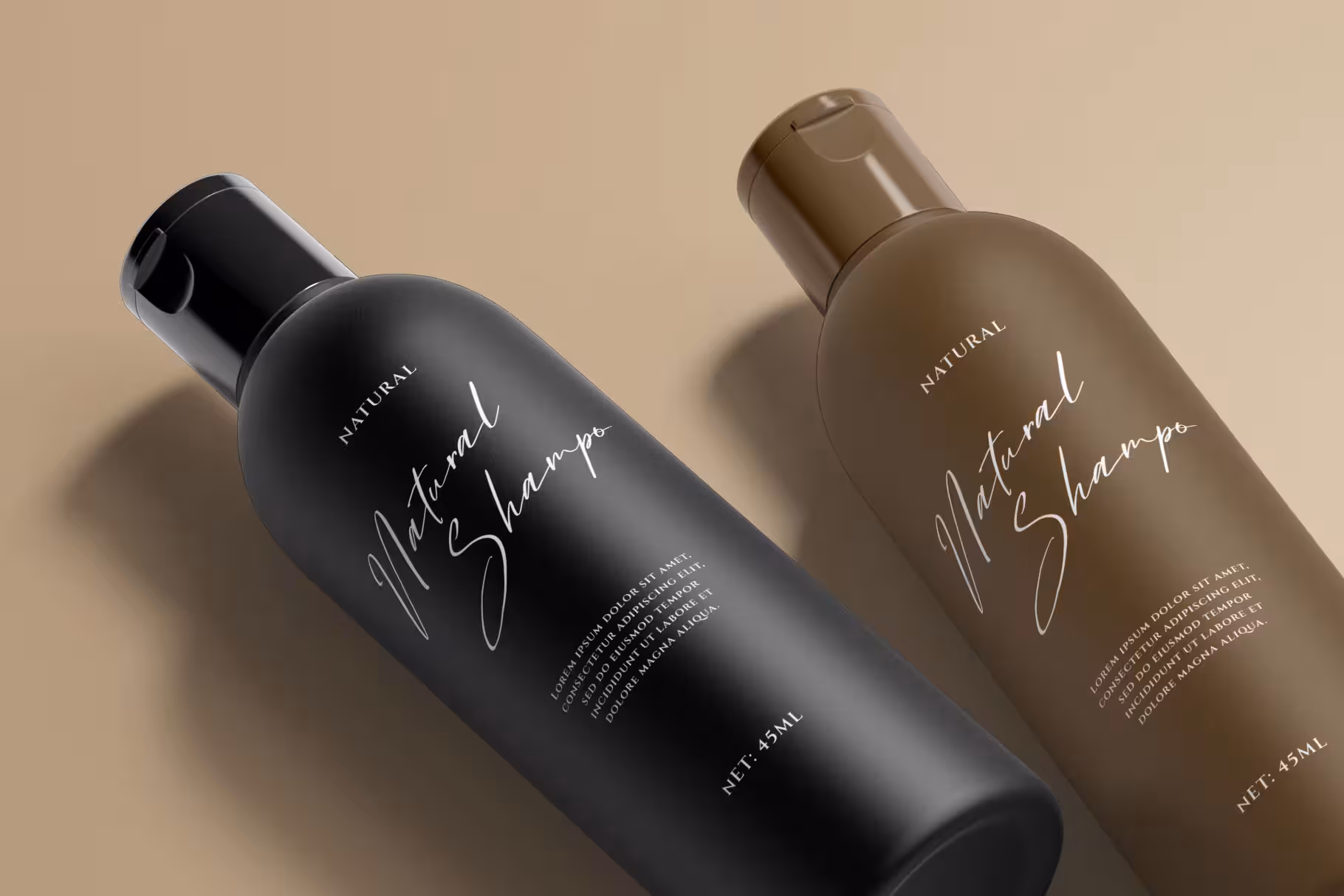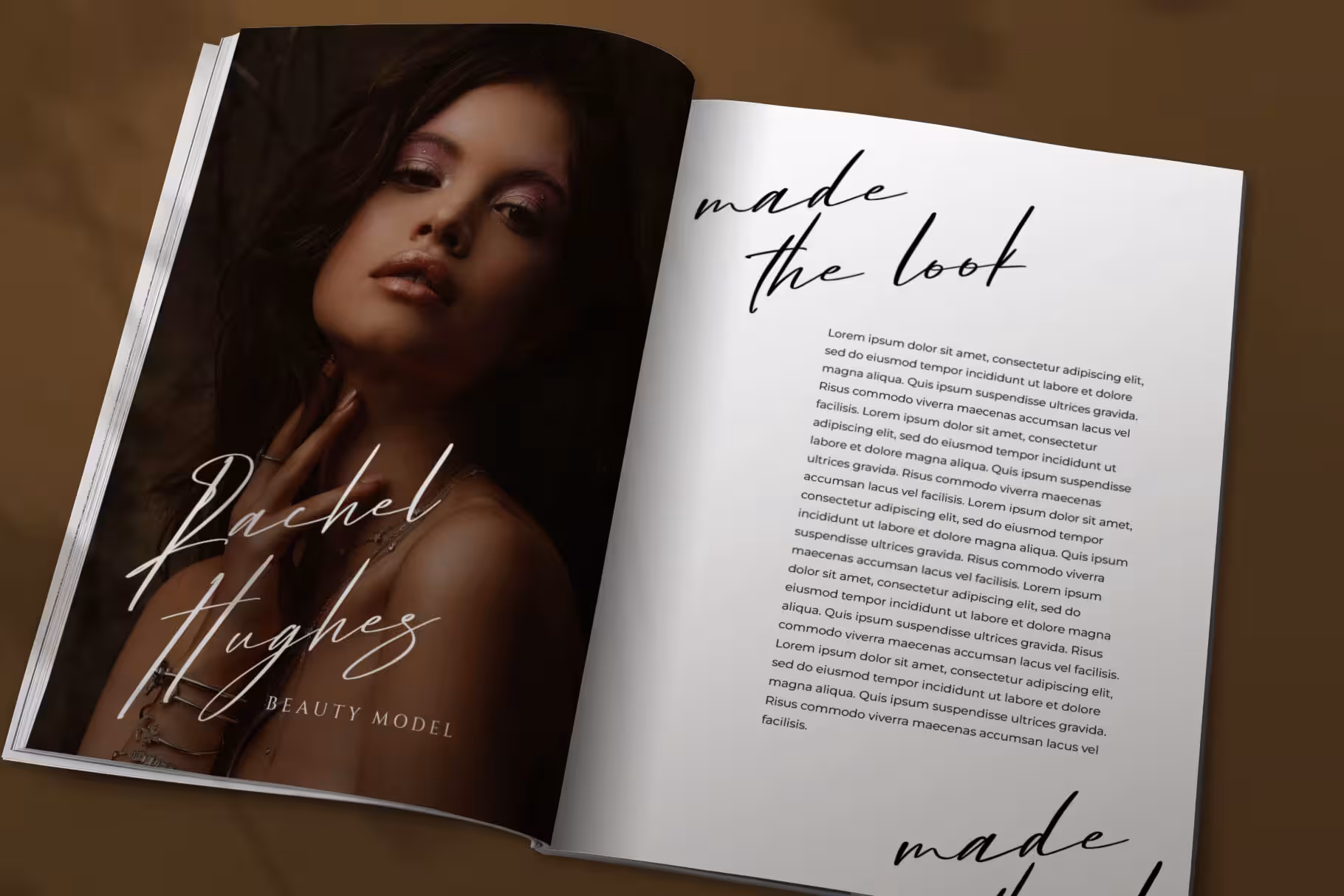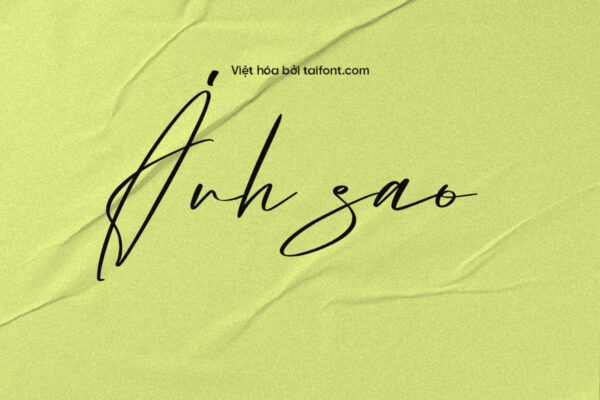
Giới thiệu về Font TF Remundy Việt hóa
TF Remundy Việt hóa là một font chữ viết tay (script font) nổi bật với những đường nét thanh lịch, tự nhiên và đầy phong cách, mang đến vẻ đẹp vừa tinh tế vừa cá tính. Font này gợi cảm giác như một chữ ký được viết tay một cách tỉ mỉ, có hồn, tạo nên sự độc đáo và riêng biệt cho mọi thiết kế. Sự kết hợp giữa nét thanh thoát và sự uyển chuyển làm cho Remundy trở nên rất cuốn hút.
Với sự duyên dáng và tính thẩm mỹ cao, Remundy là lựa chọn lý tưởng cho các thiết kế muốn truyền tải sự tinh tế, cá nhân hóa và một chút nghệ thuật:
- Thiết kế tạp chí: Hoàn hảo để sử dụng cho các tiêu đề phụ, lời dẫn, trích dẫn hoặc các bài phỏng vấn trong các tạp chí thời trang, phong cách sống, nghệ thuật hoặc du lịch. Nét viết tay của Remundy sẽ làm cho nội dung trở nên sống động, gần gũi và thu hút độc giả, tạo điểm nhấn nghệ thuật trên các trang báo.
- Thiết kế thời trang: Lý tưởng cho các nhãn mác quần áo, tem nhãn phụ kiện, hoặc các chi tiết nhỏ trong lookbook. Font này giúp truyền tải vẻ đẹp thanh lịch, độc đáo và dấu ấn của nhà thiết kế, nâng tầm giá trị thương hiệu.
- Thiết kế thư mời và thiệp: Phù hợp cho các loại thư mời sự kiện, tiệc tùng, khai trương hoặc thiệp mời cá nhân. Font này giúp thư mời trở nên sang trọng, cao cấp và đầy tính nghệ thuật.
Với TF Remundy Việt hóa, bạn có thể dễ dàng thổi hồn nghệ thuật, sự tinh tế và cá tính vào các thiết kế, tạo ra những sản phẩm không chỉ đẹp mắt mà còn đầy cảm xúc và sức hút đặc biệt.